汉仪字库4月份推荐字体大全
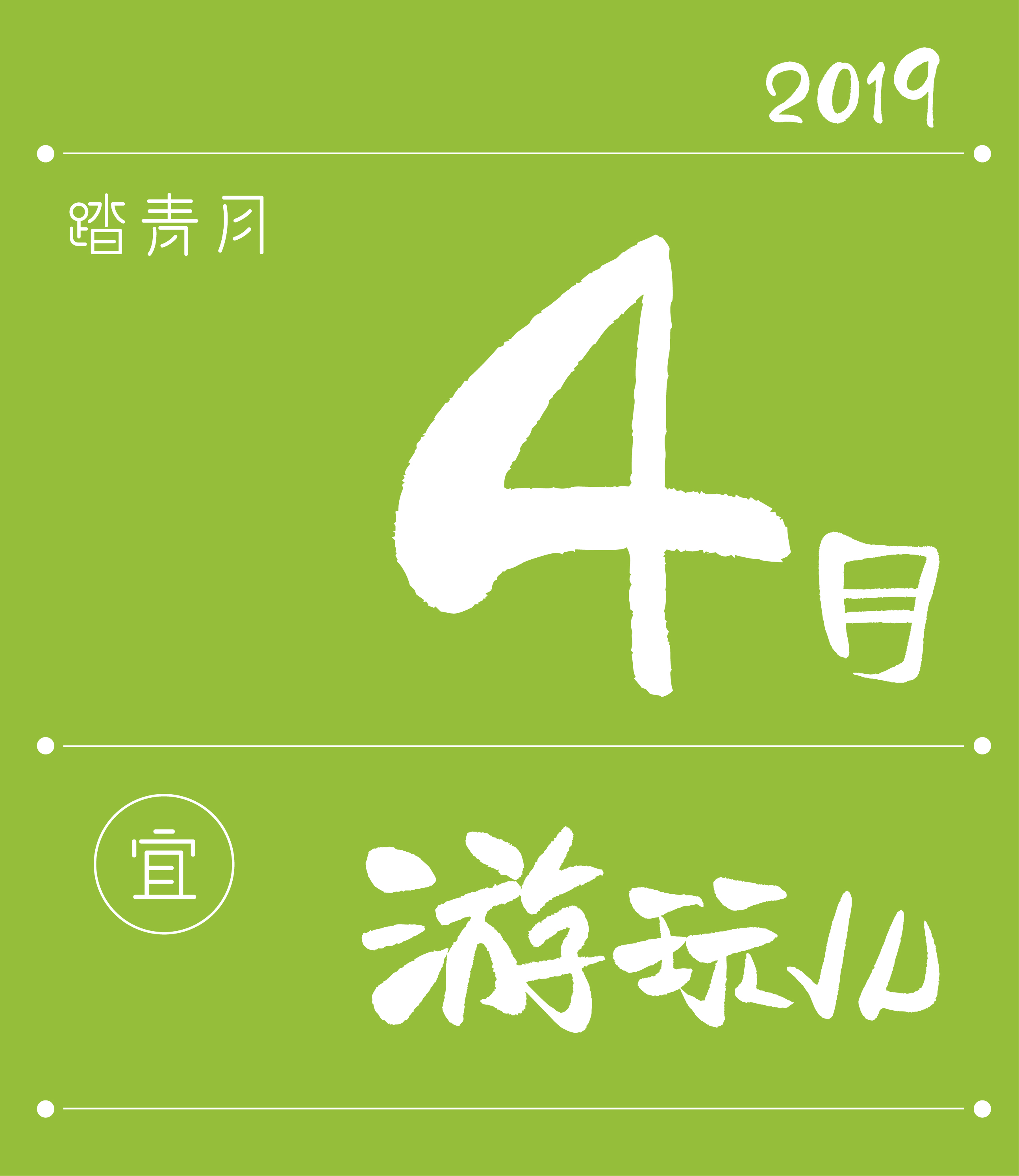
春暖花开的4月,
汉仪字库 × 微博美学博主 #泥二码#
汉仪二码墨书,
青青来袭~
一个爱嘎哈就嘎哈的东北小姐姐,
让每一个字都妙趣横生!
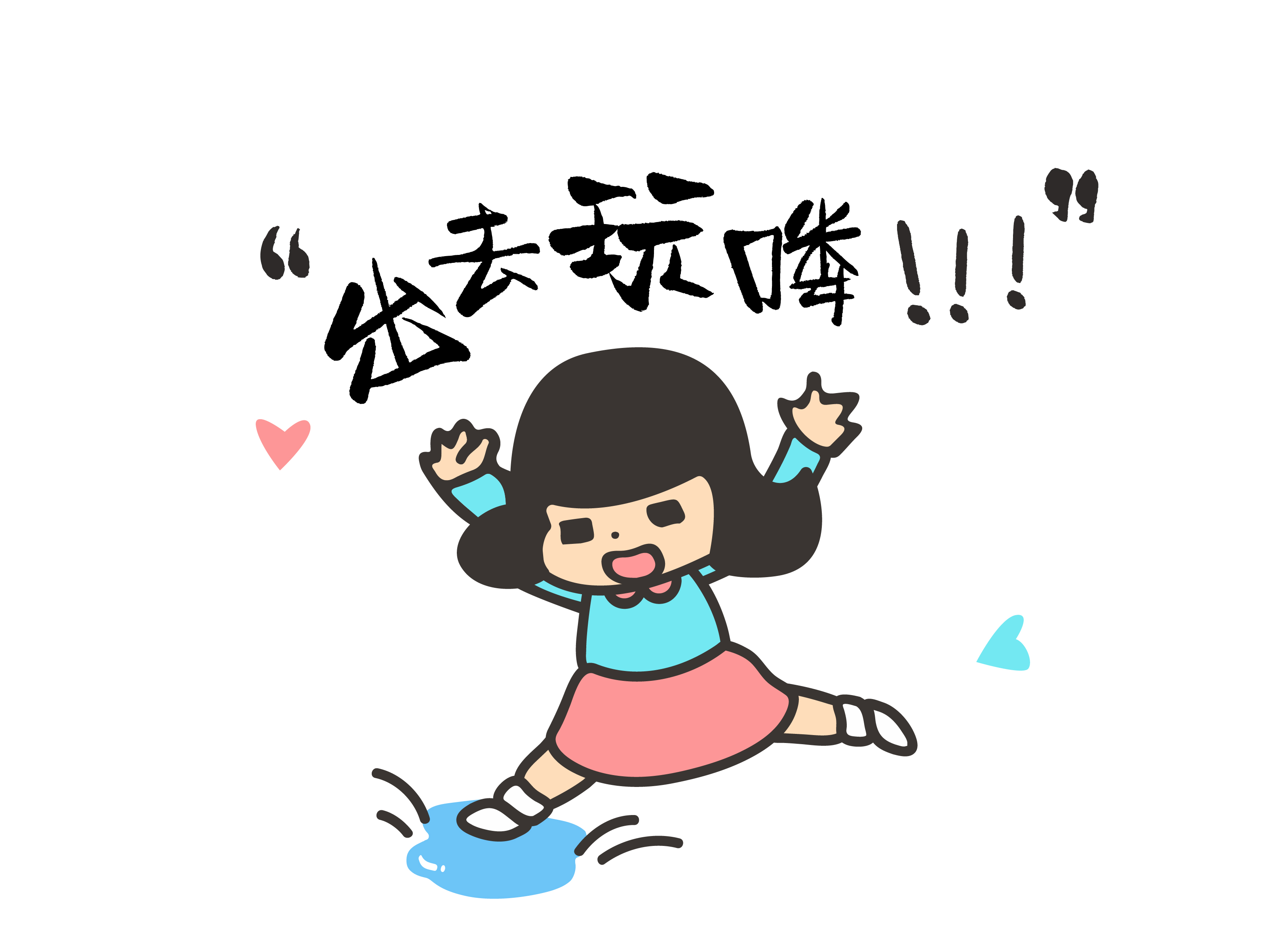
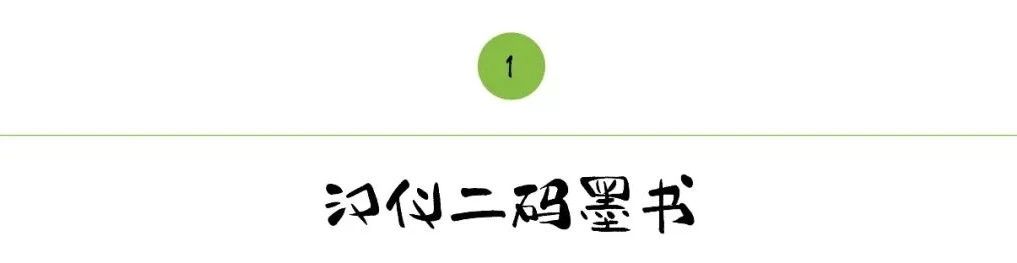
汉仪二码墨书是一款可爱乖巧,又饱含力量的创意书写体,设计师赋予了这款字体新奇大胆的结构,像一个搞怪的小女孩,机灵而又张扬、直爽。
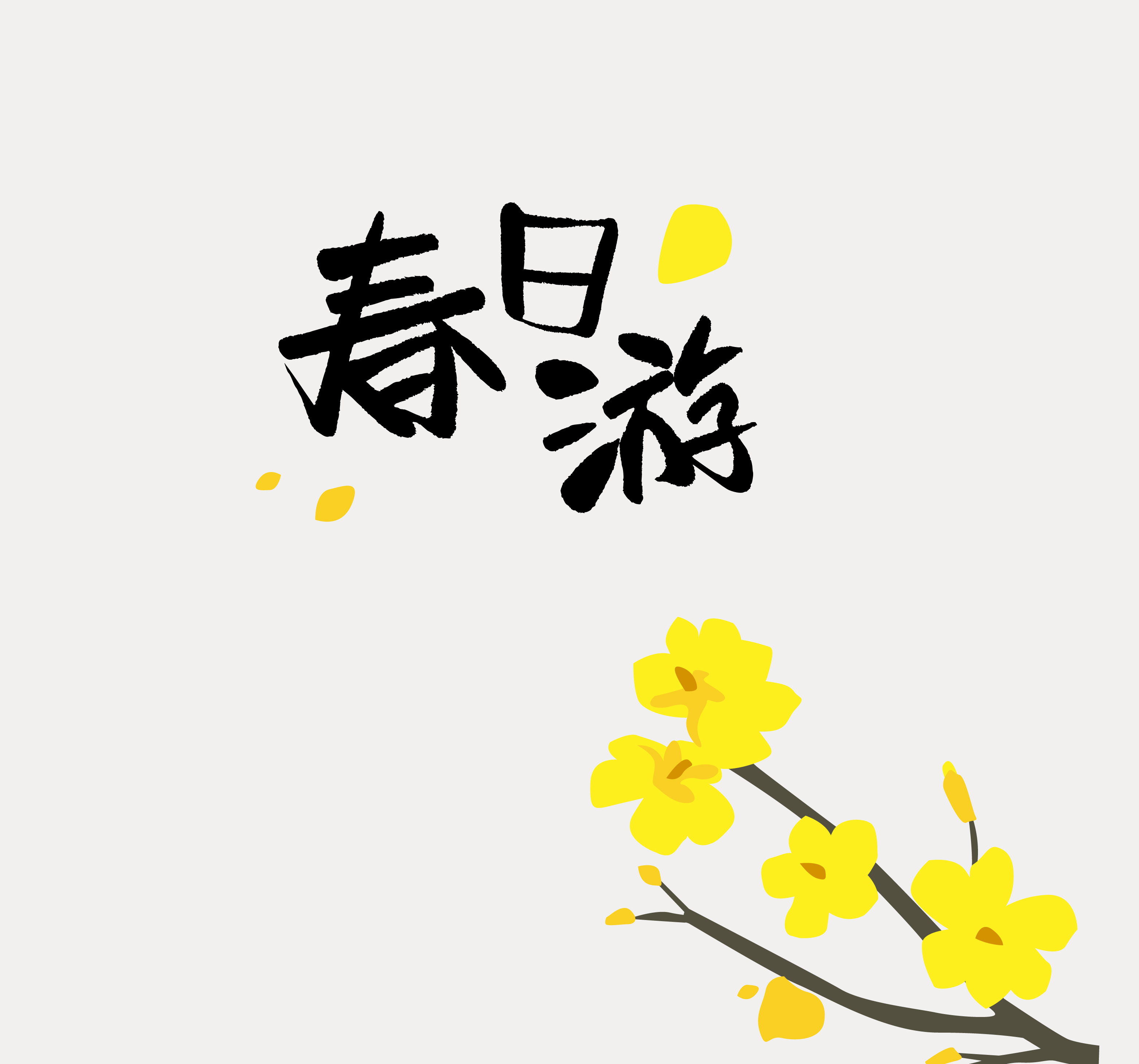
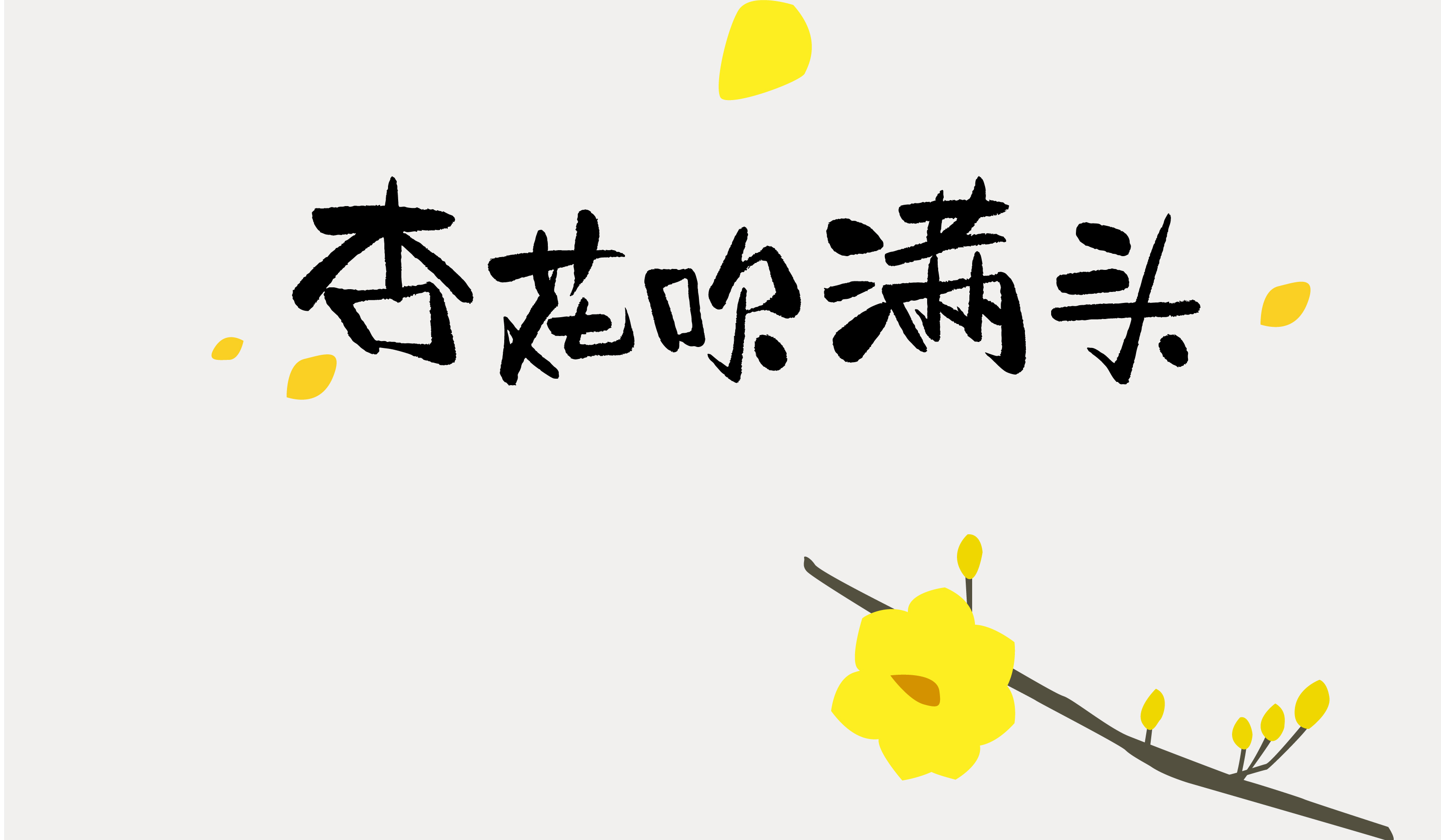
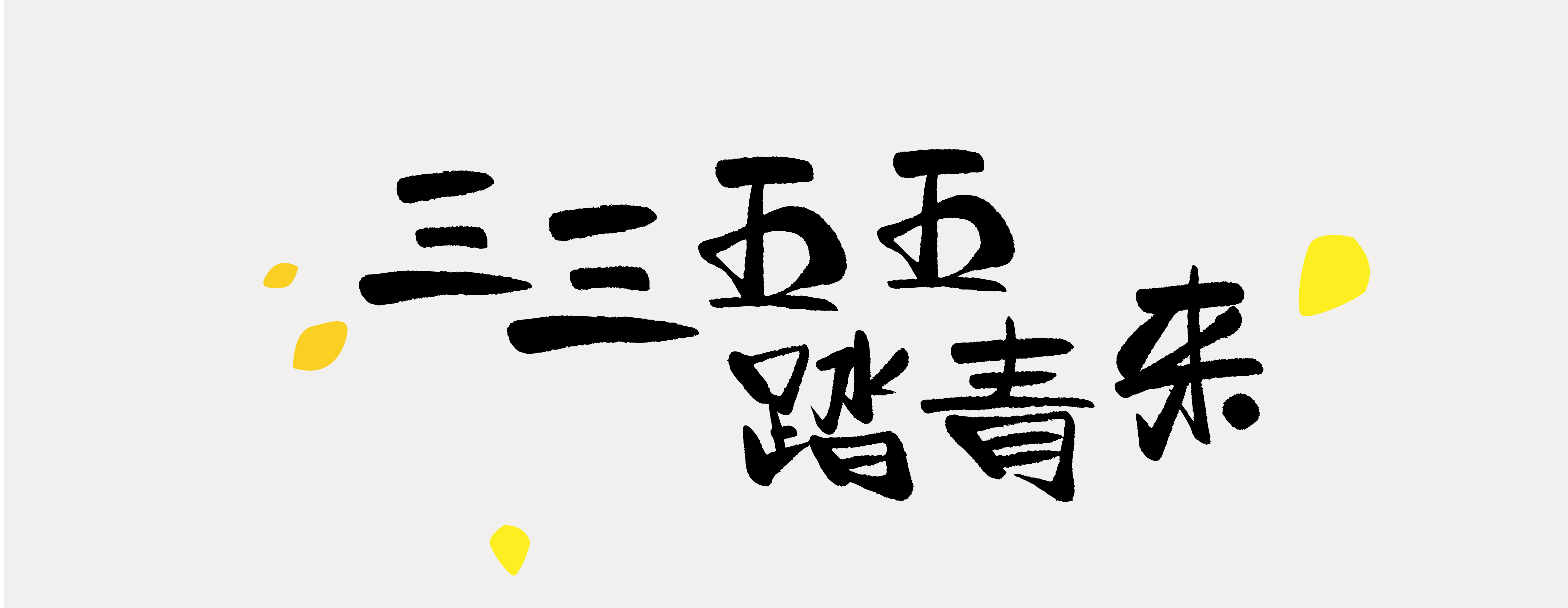
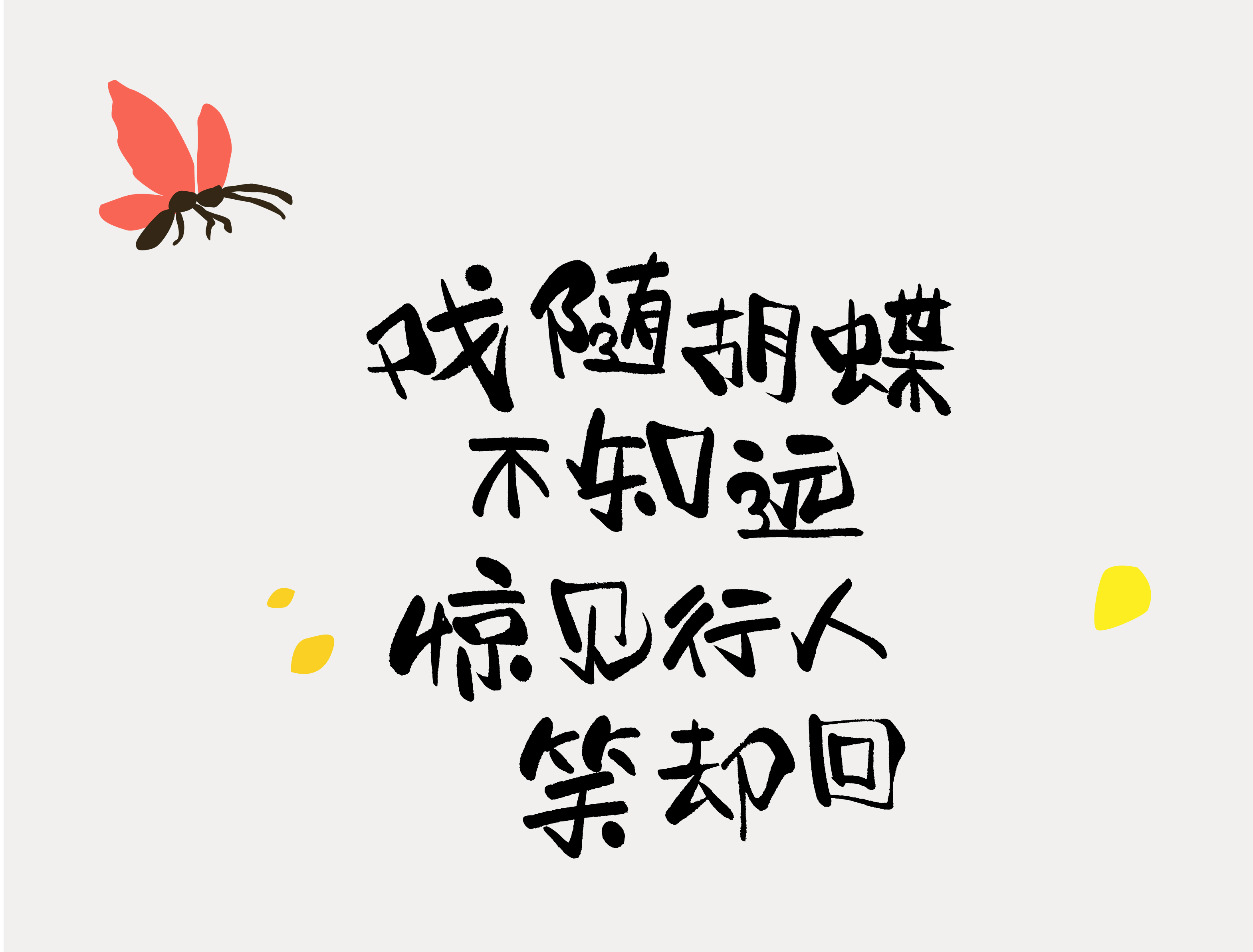
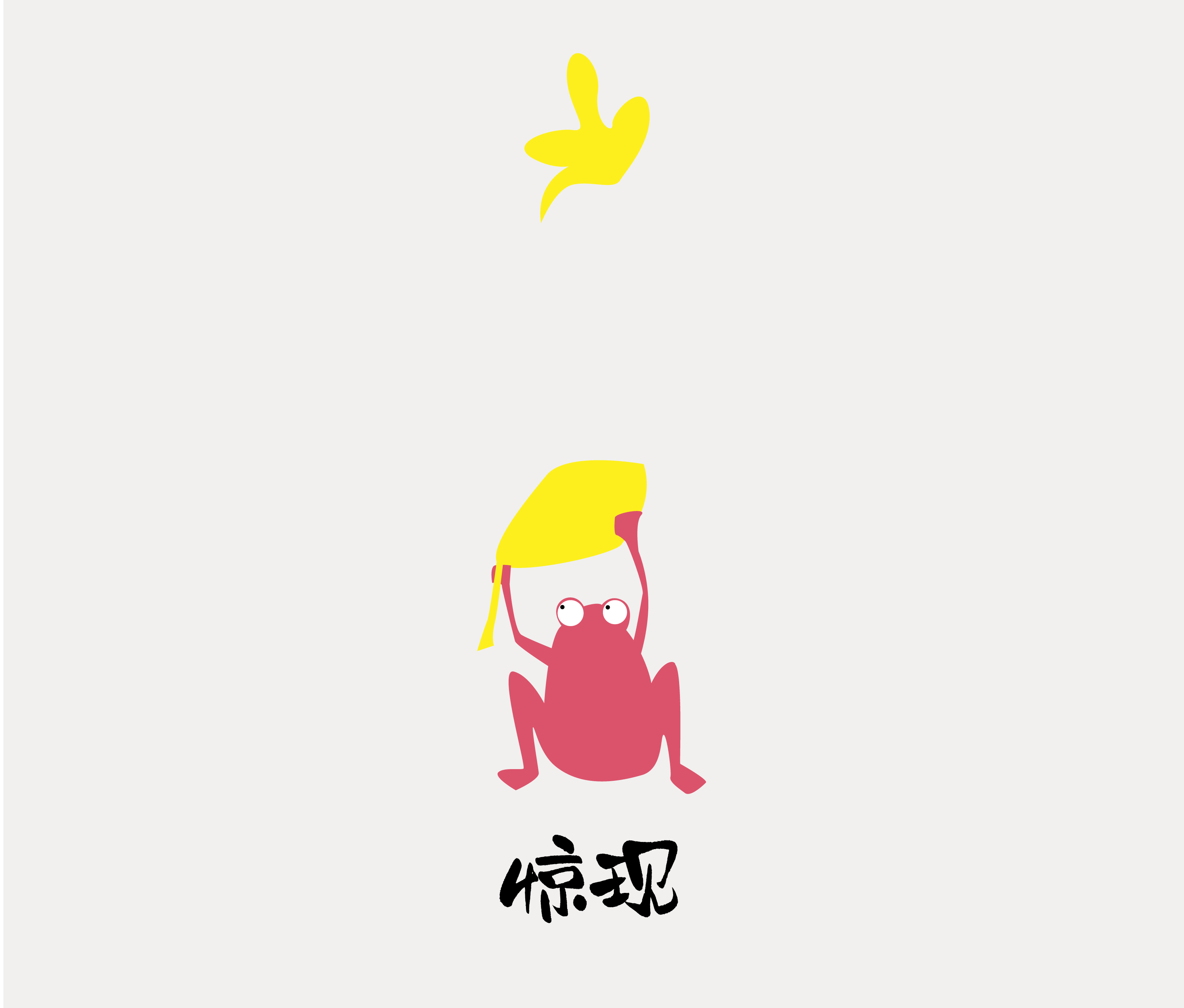
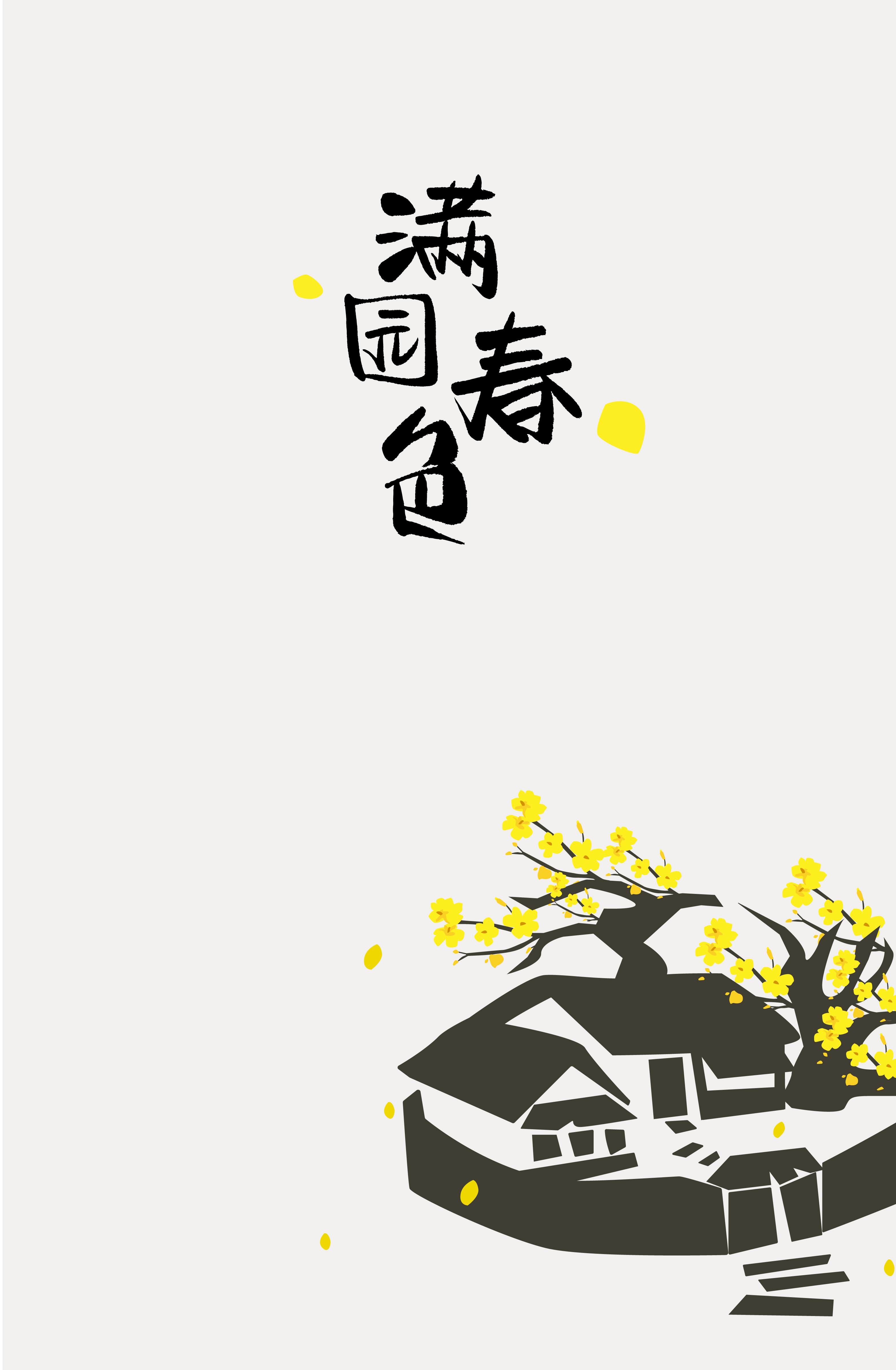
汉仪字库 × 书法家#李国兴#
汉仪李国兴行楷,
吹进四月的春天里~
汉仪李国兴行楷是由书法家李国兴创作的一款行楷,这款字体边缘质朴,笔触细节丰富,有一种古拙的韵味。